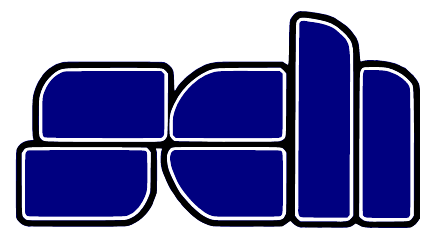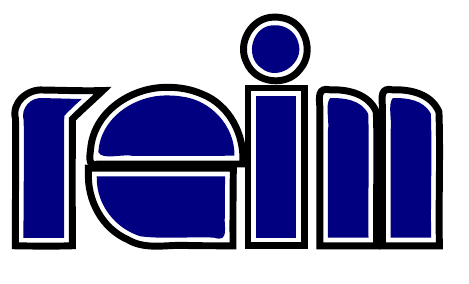
Ich würde auch sagen, wenn dies eine Schrift ist, fresse ich nicht nur meinen Besen, sondern die Kehrsxchaufel gleich mit.
Das ist eindeutig gezeichnet, und noxch dazu von jemandem, der entweder das falschwe Programm dazu genutzt hat, oder mit seinem Programm nur sehr rudimentär zurecht kommt. Man schaue nur auf die schlechten Übergänge von Radien zu Geraden.
Das soll eine Schrift sein.
Wurde vor langer Zeit von einem Bekannten erstellt, der jedoch nicht mehr erreichbar ist.
Ich habe leider den Text nur eingescannt bekommen.
Die Umrandung könnte auch nachträglich erstellt worden sein.
Da habe ich leider keine Kenntnis dazu.
Hab noch einen früheren Scan, wo die Schrift etwas anders aussieht. Soll aber angeblich die gleiche sein.
Die Beispiele sehen mir in vielen Details so aus, als wären sie in einem Vektorprogramm von Hand zusammengedengelt worden. Bei einer bestehenden Schrift hätte sich der Ersteller wahrscheinlich ein klein wenig mehr Mühe gegeben.